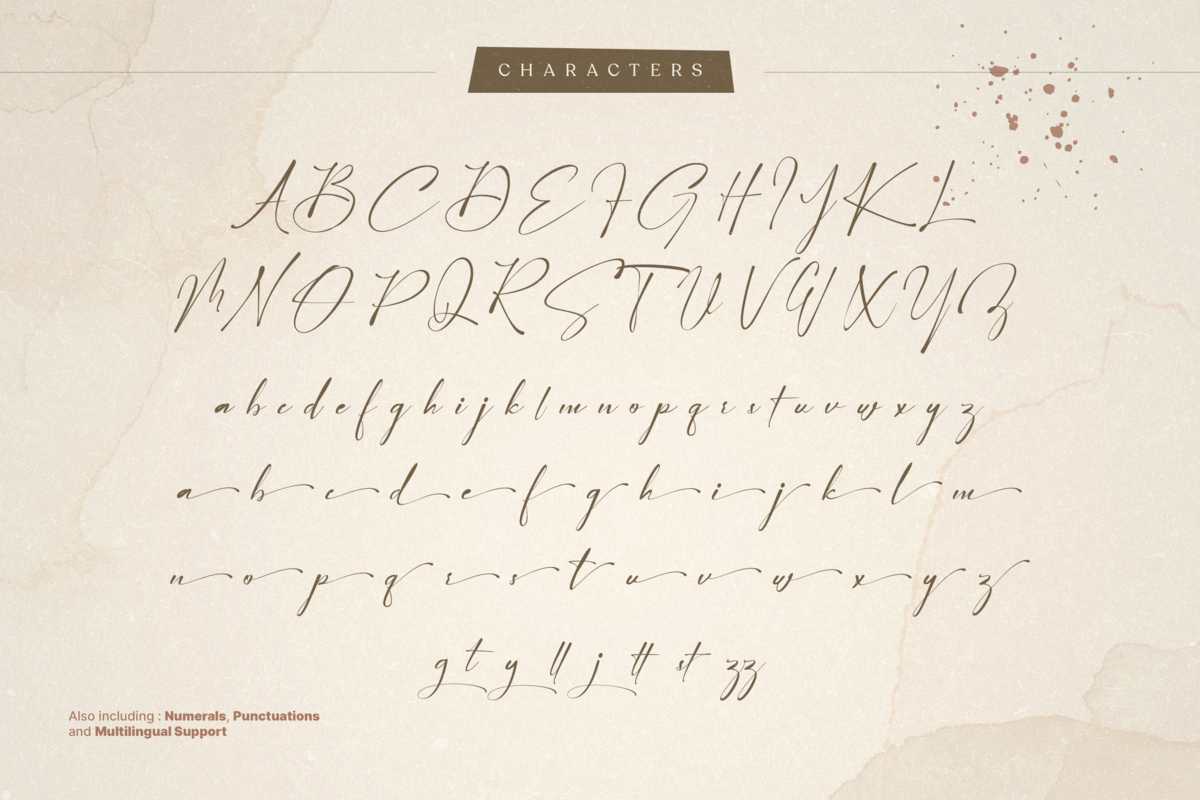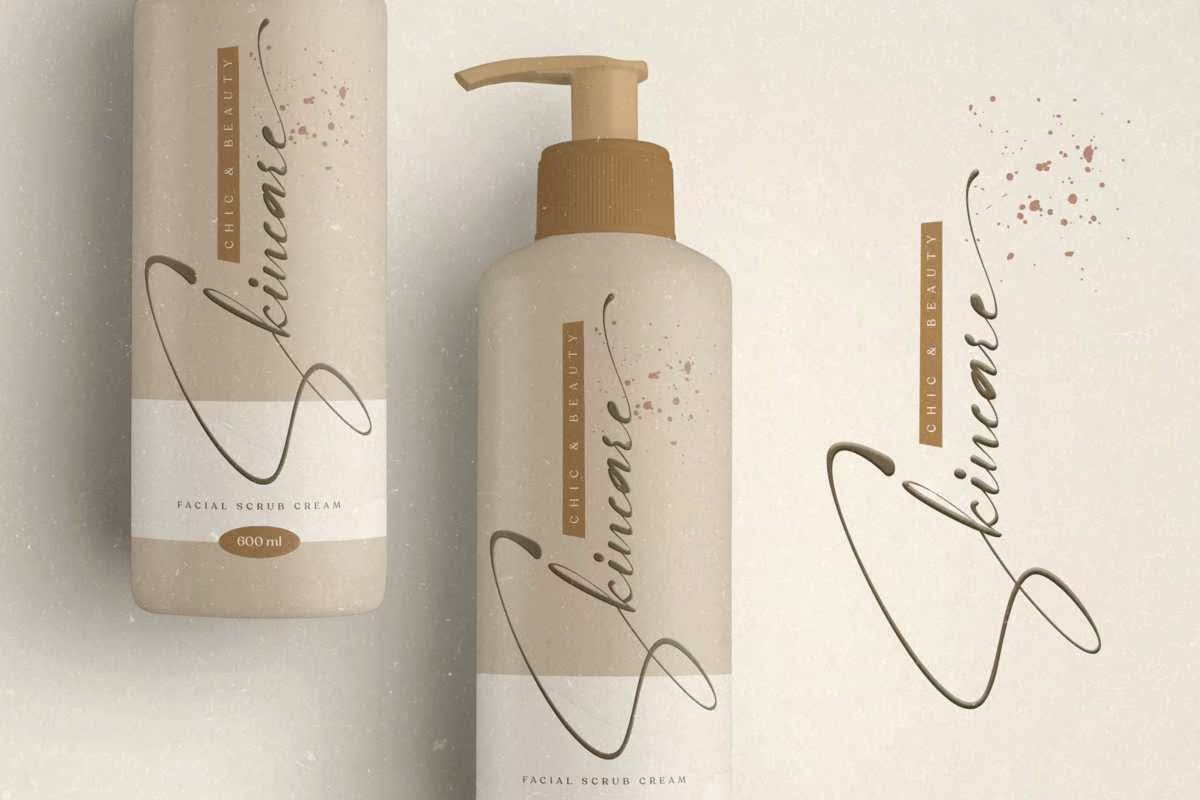
自然和风格签名,具有丰富的灵魂。完善各种不同的项目,如徽标和品牌、邀请函、文具、婚礼设计、社交媒体、广告、产品包装、产品设计、标签、照片、水印、特殊符号或任何东西。包括大写、小写、斜杠、数字、标点符号、,多语言支持,可更换花套,并带有末端洗涤。自然和风格签名,带有灵魂的印记。完善不同的项目,如徽标和品牌、邀请函、文具、婚礼设计、社交媒体、广告、产品包装、产品设计、标签、照片、水印、特殊物品或任何东西。包括大写,小写、斜杠、数字、标点符号、多语言支持和带尾端斜杠的可选花格。